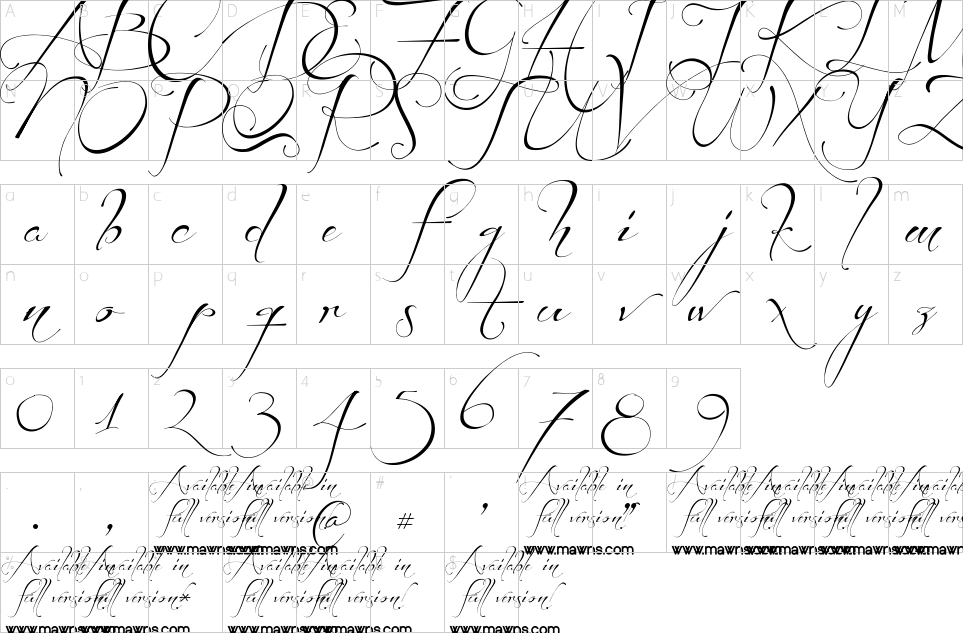
Fonte gratuita ‘Before The Rain’ para Windows e Mac está disponível aqui. Esta fonte foi criada pelo designer sueco Måns Grebäck, que não foi revelado aqui. ‘Before The Rain’ é uma fonte elegante e versátil, ideal para design gráfico, publicidade e web. É uma escolha ótima para aqueles procurando por uma fonte fresca e moderna sem ter que gastar dinheiro. Com mais de um milhão de downloads, é claro que essa font recebeu elogios de designers ao redor do mundo. Se você está procurando por uma fonte moderna, agradável e disponível gratuitamente, não perca tempo e baixe ‘Before The Rain’ agora.